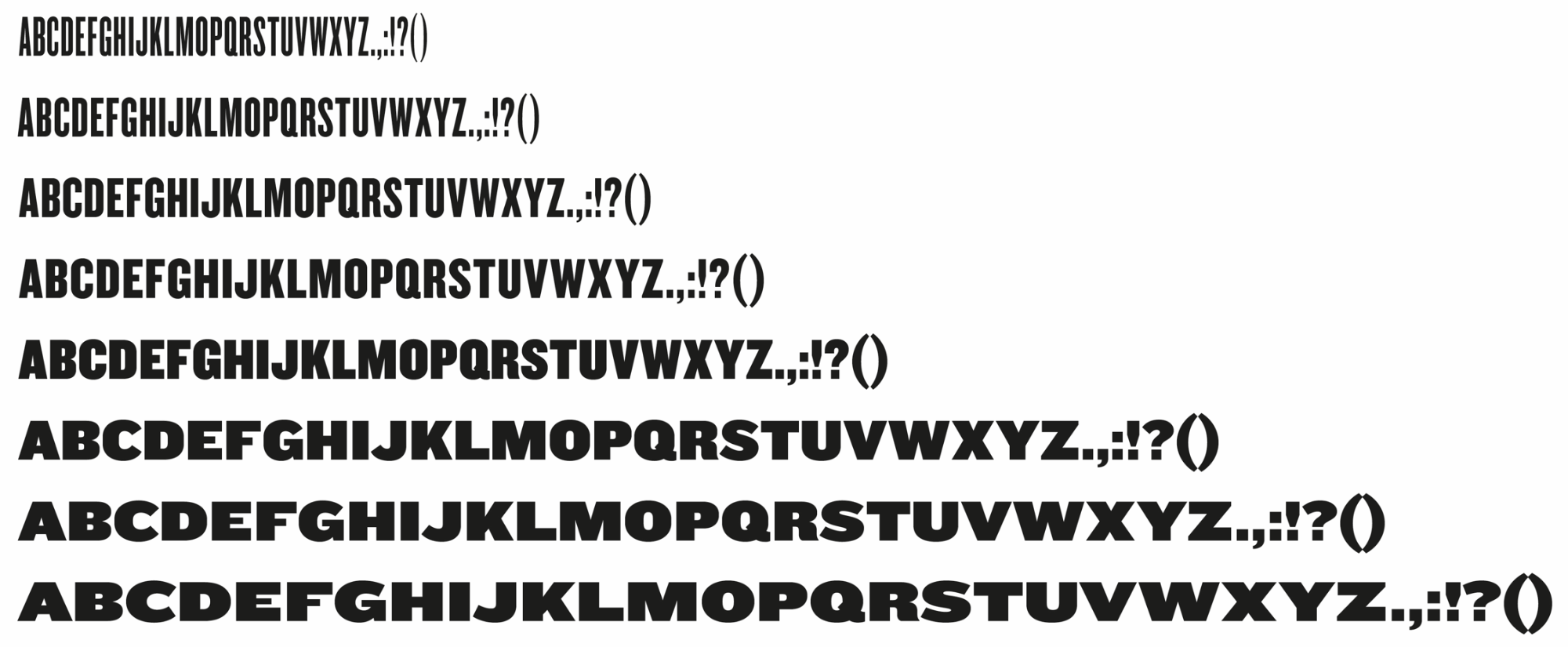
Bitte um Schriftidentifikation: serifenlose Display-Schriftfamilie (Stil: Grotesk spätes 19. Jh.)
Die Schriftfamilie ist ähnlich der Knockout von Hoefler&Co. Könnt Ihr mir sagen, um welche Schrift es sich handelt?
Es wurde mir von einer Designagentur geliefert. Leider will die Agentur mir keine Auskunft geben, um welche Schrift es sich handelt. Die Quelle des Schriftbeispiels kenne ich daher auch nicht.
Die Knockout? Gerade noch einmal stichprobenartig verglichen und keine Abweichungen ausmachen können.